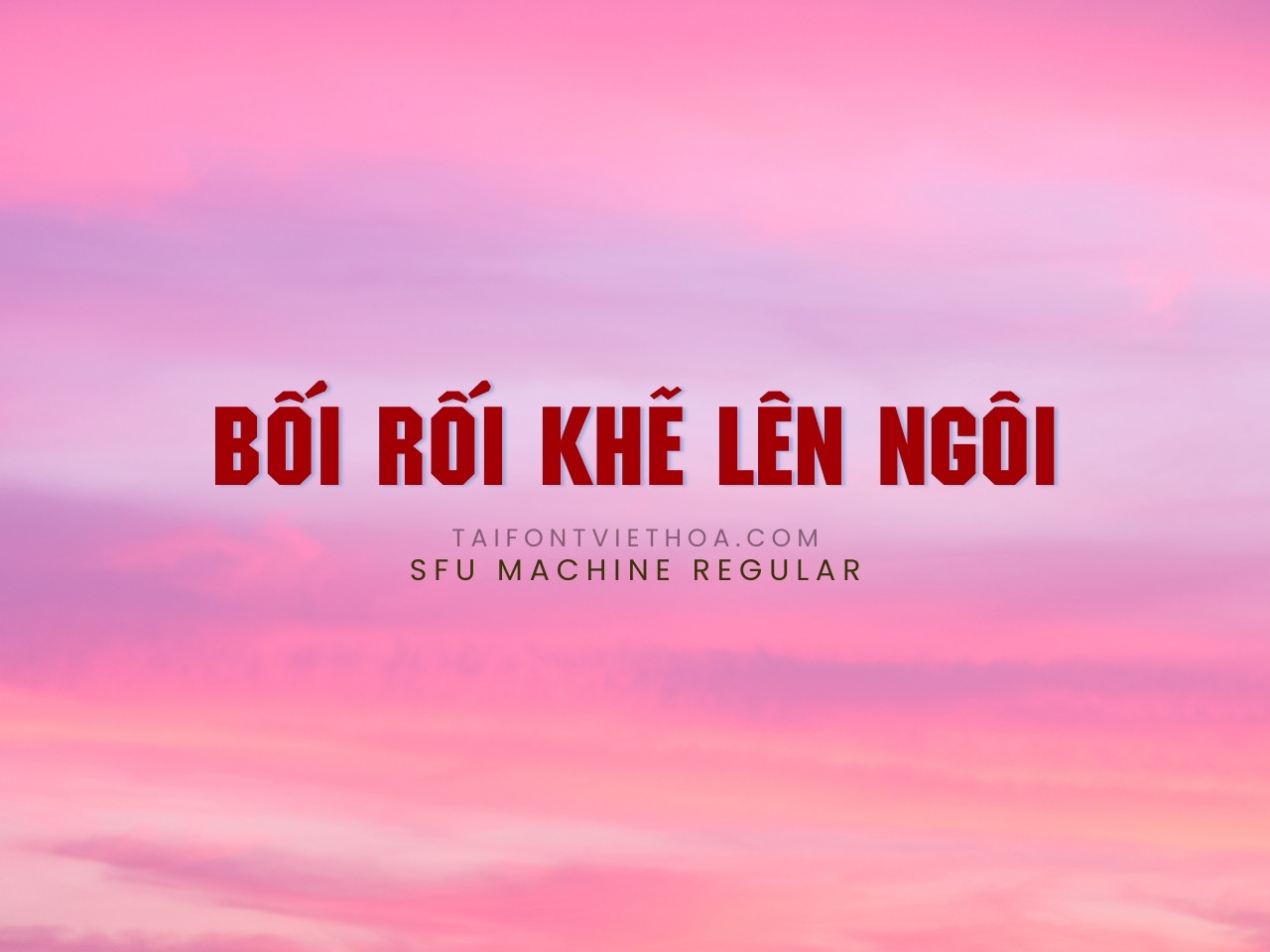
Font việt hóa SFU Machine
Giới thiệu về SFU Machine – Kiểu chữ công nghiệp, mạnh mẽ và sắc nét
SFU Machine là phiên bản Việt hóa của font Machine, một họ sans‑serif mang đậm phong cách công nghệ – retro, lần đầu được Monotype phát hành vào năm 1997. Font gốc được tạo ra trên nền Macromedia Fontographer, phiên bản Regular có khoảng 366 ký tự tiêu chuẩn. Bản Việt hóa SFU Machine được đăng tải ngày 30/09/2023 trên FontTiếngViet.com bởi Nguyễn Quỳnh Trâm Anh, tuy tác giả Việt hóa cụ thể chưa được xác minh rõ ràng.
Phiên bản Việt hóa không chỉ hỗ trợ đầy đủ bảng ký tự tiếng Việt chuẩn Unicode, mà còn tương thích với bảng Latin Extended, giúp sử dụng linh hoạt cho các ngôn ngữ như Anh, Pháp, Đức… . Sự tinh chỉnh cẩn thận đã giữ lại các nét góc cạnh đặc trưng, đảm bảo dữ liệu Unicode đầy đủ và rõ nét trên mọi nền tảng.
Thiết kế kỹ thuật & ứng dụng đa dạng của SFU Machine
SFU Machine thuộc dòng sans‑serif display: có nét chữ chắc chắn, góc cạnh mạnh và chiều cao x (x‑height) cao, mang lại cảm giác sắc bén và hiệu ứng kỹ thuật. Các ký tự như “E” và “F” có chân ngang dài, tạo sự cứng cáp, rõ ràng. Đuôi chữ tròn, dễ phân biệt “l” với số “1”.
Ứng dụng phù hợp:Thiết kế tiêu đề banner quảng cáo kỹ thuật, poster phim – sự kiện mang phong cách retro công nghệ, thiết kế logo startup, biển hiệu, bao bì sản phẩm công nghiệp mạnh mẽ, áo thun, ảnh kỹ thuật số.
Ngành nghề phù hợp:Công nghệ – IT, truyền thông quảng cáo, thiết kế đồ họa, marketing kỹ thuật số, sản phẩm công nghiệp, startup – thương hiệu kỹ thuật số, lĩnh vực chế tạo – máy móc, ngành game.